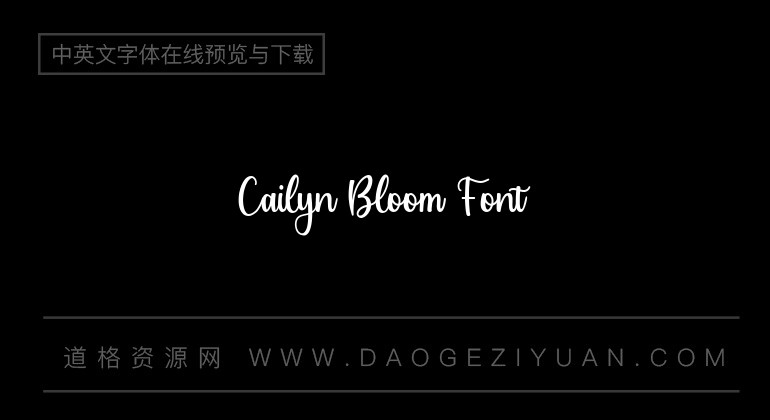
Cailyn Bloom Font
Cailyn Bloom Font 是一款流行的手写风格字体,适用于多种设计项目,如印刷品、海报、包装设计、插图等。这款字体由设计师Sarid Ezra于2018年创建,其特点是笔画流利、优美、自然,带有一些笔画的颤动,使其看起来更加手写风格。 Cailyn Bloom Font 包含大写字母、小写字母、数字和标点符号,支持西欧语言。该字体的可读性非常好,适合用于标题、标语、引言等需要强调的文本。此外,该字体还带有一些额外的装饰元素,如连字、粗体、斜体等,可以为设计师提供更多的创意选择。 总的来说,Cailyn Bloom Font是一款非常有特色的手写风格字体,适用于多种设计场景,非常受设计师的欢迎。
Cailyn Bloom Font是一款非常不错的手写艺术字体,具有很好的视觉感,适合于文化类的宣传设计、商业类品牌的广告和产品包装设计以及个性化文字排版等较多场景。